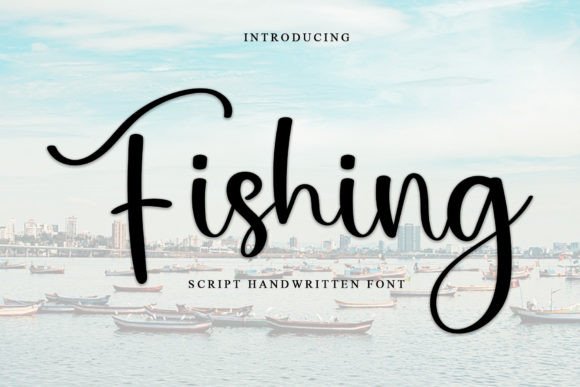
Fishing
Trouver les bons éléments de conception peut être un défi, mais Fishing propose une collection exceptionnelle qui rehausse instantanément votre travail.
Que vous créiez des produits POD (impression à la demande), des invitations de mariage ou des visuels pour les réseaux sociaux, Fishing est un choix idéal.